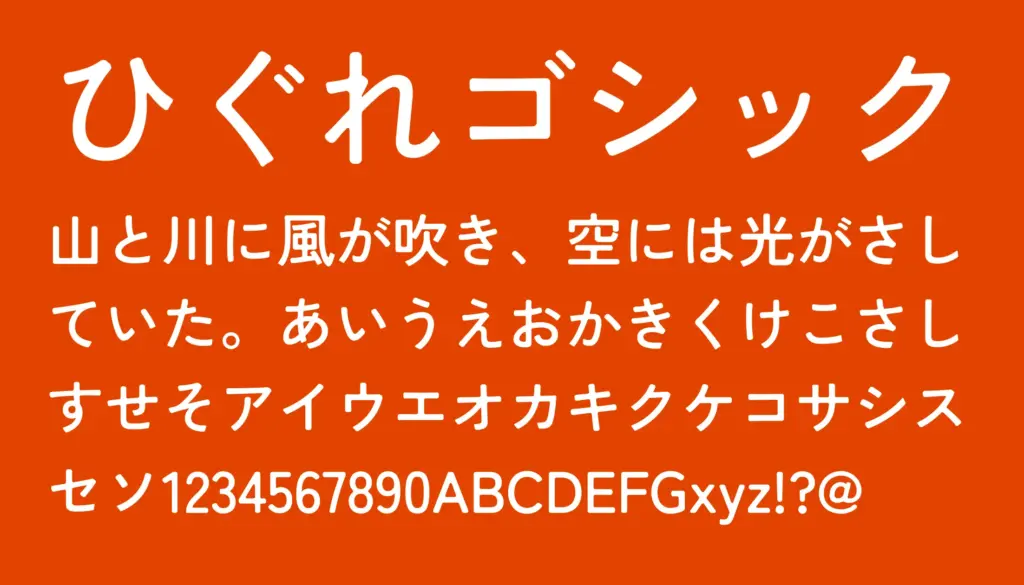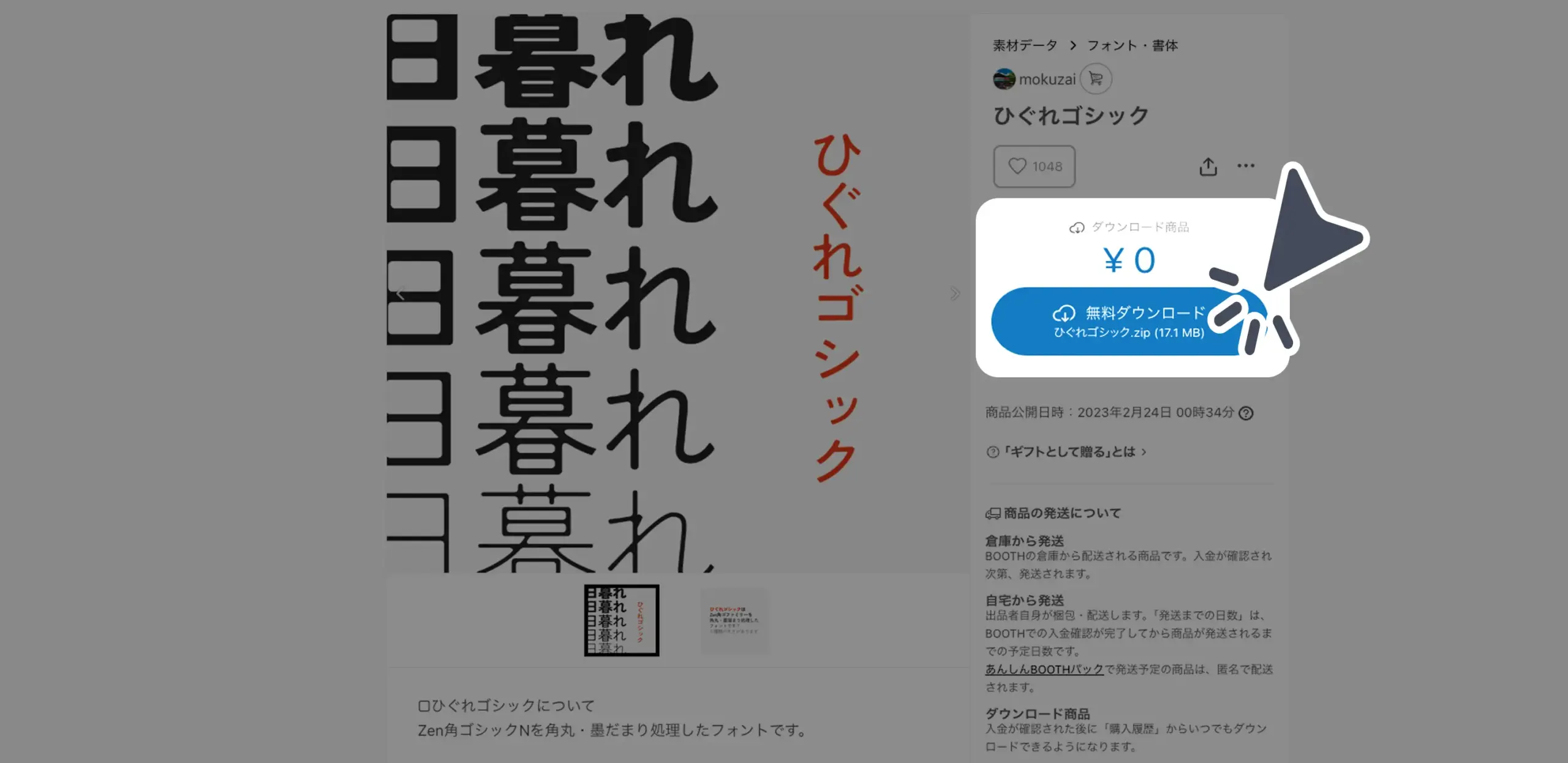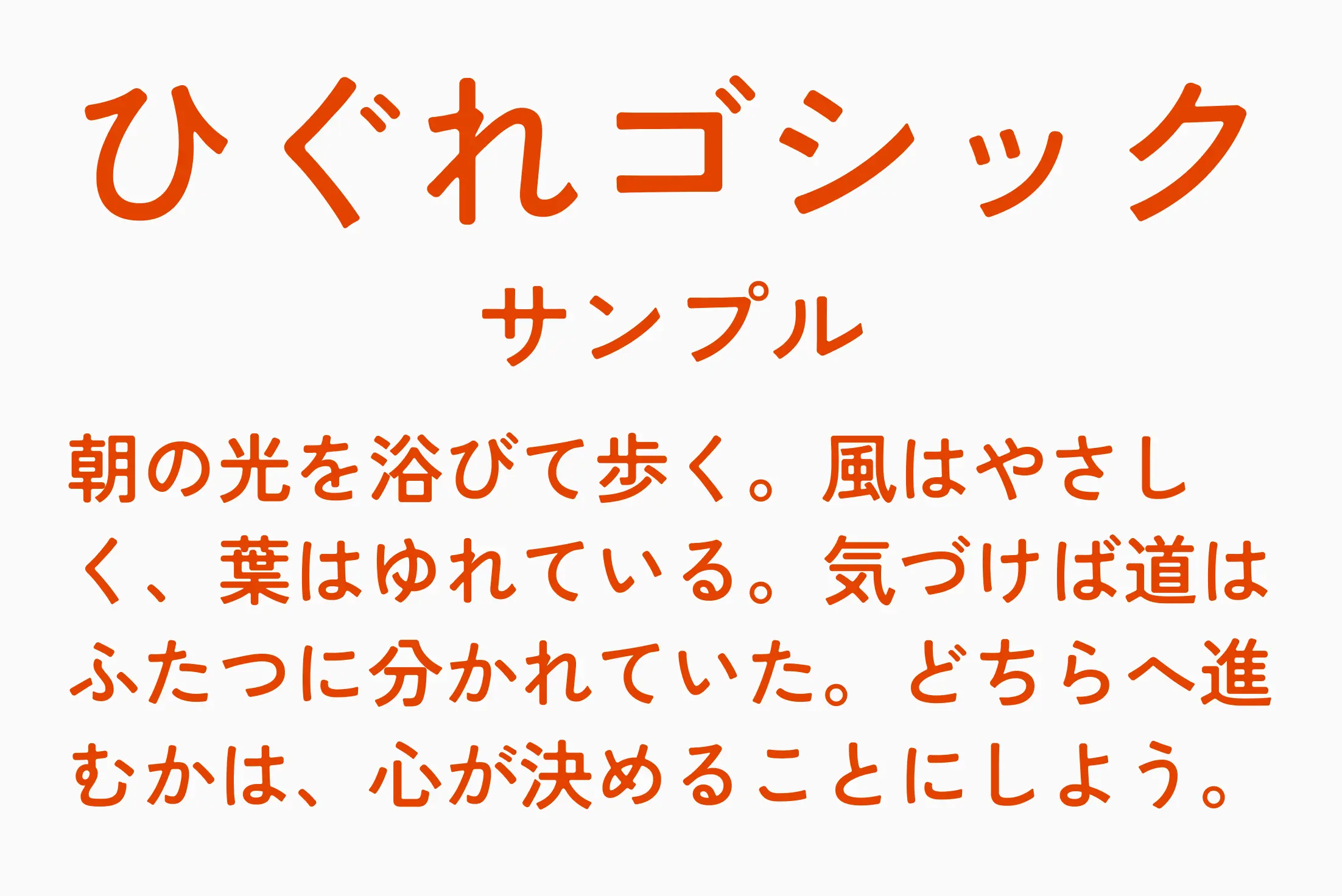
やわらかな丸ゴシックに墨だまりのニュアンスを加えたフォントです。角の丸みと微妙なインクの溜まりが、手書き風のあたたかさを演出します。ポップで親しみやすいデザインなので、YouTubeのサムネイルやタイトル文字、ロゴ、ポスターなど幅広いシーンで活躍。
ひぐれゴシック
やわらかな丸ゴシックに墨だまりのニュアンスを加えたフォントです。角の丸みと微妙なインクの溜まりが、手書き風のあたたかさを演出します。ポップで親しみやすいデザインなので、YouTubeのサムネイルやタイトル文字、ロゴ、ポスターなど幅広いシーンで活躍。